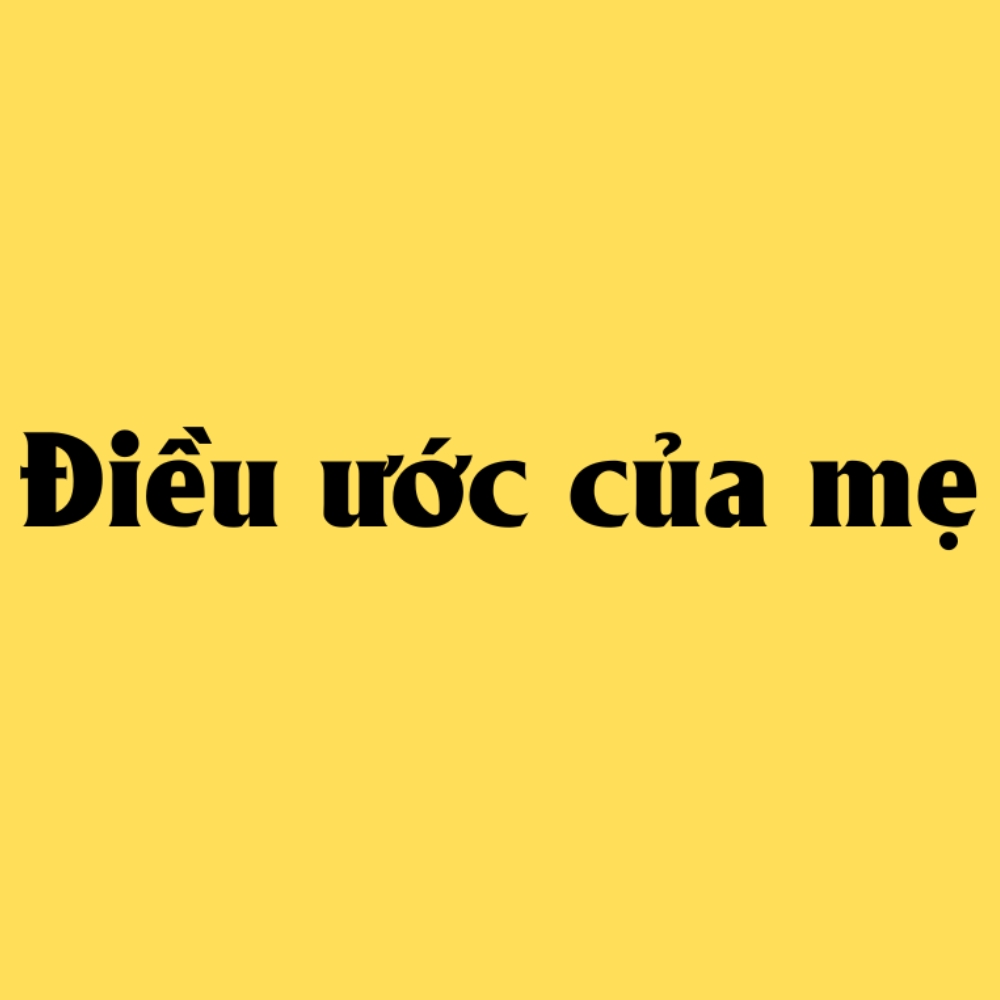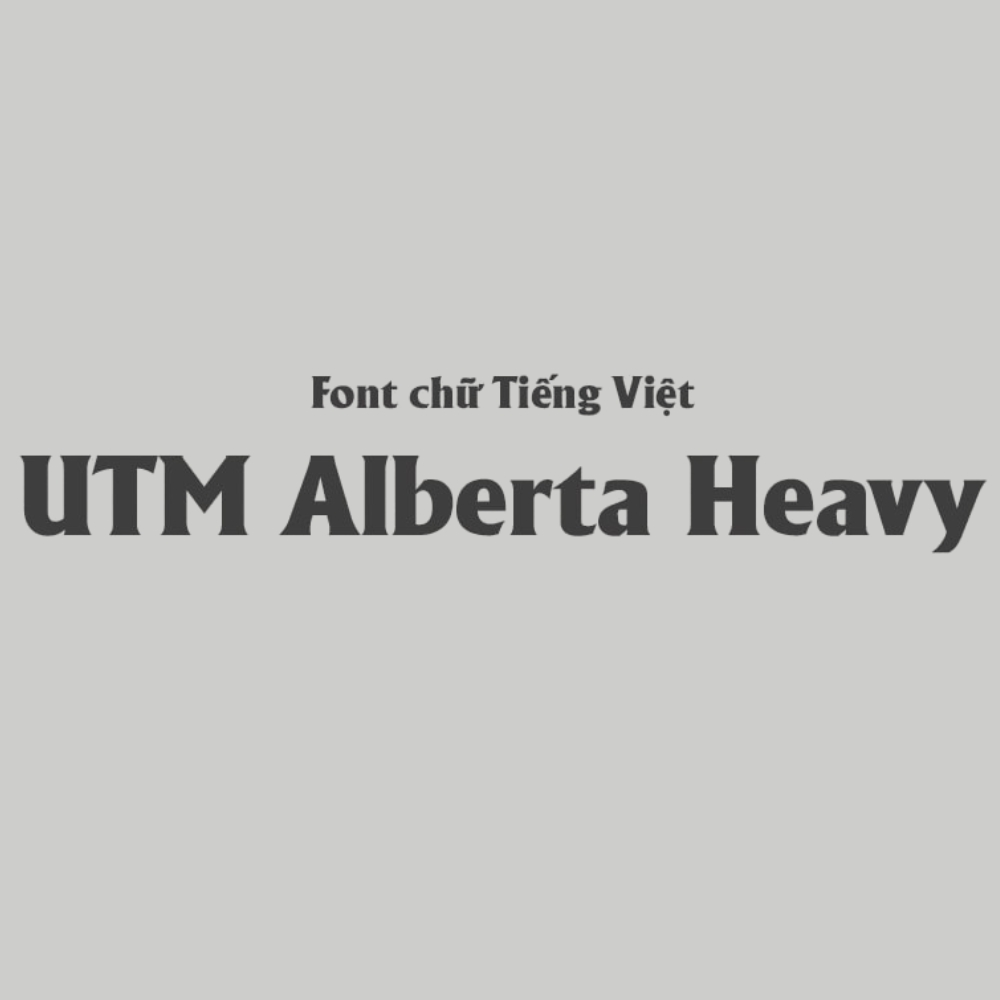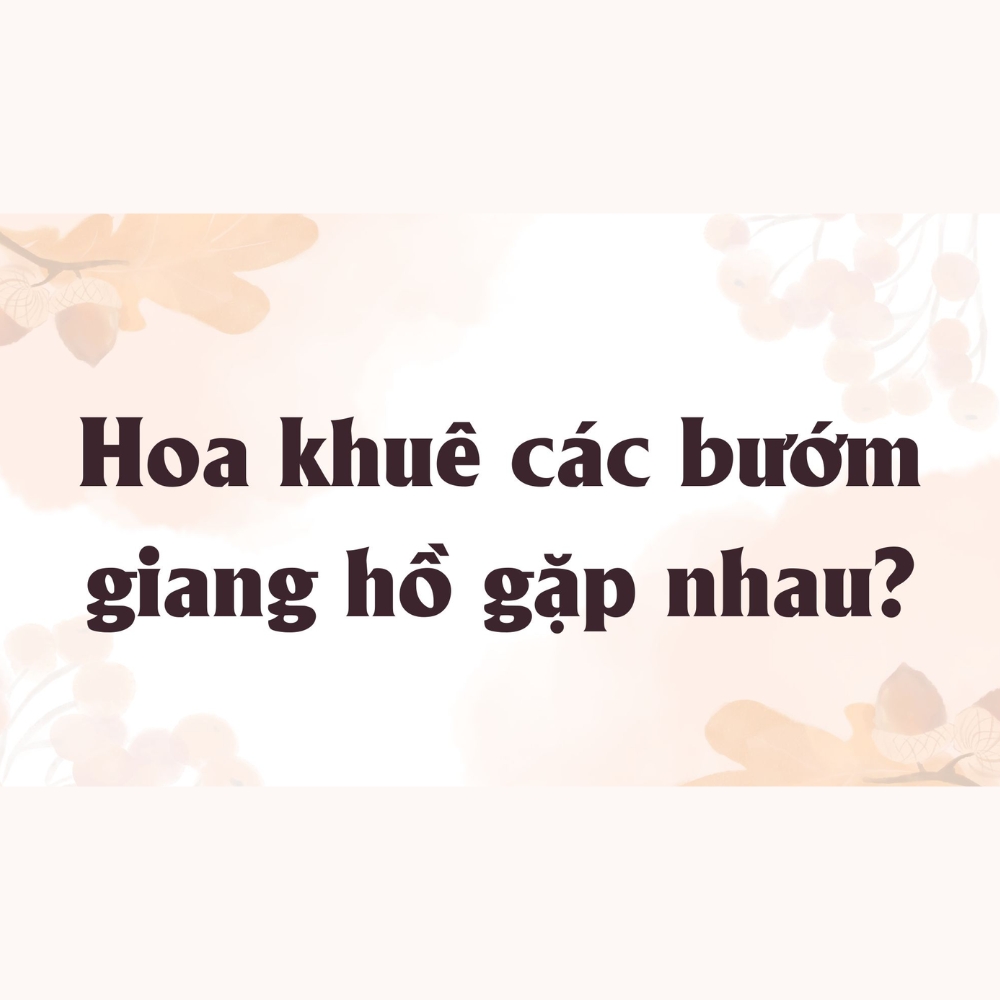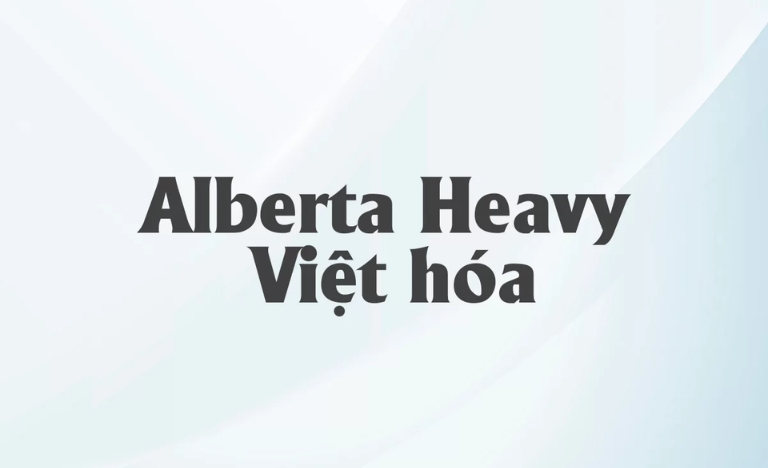
UTM Alberta Heavy là một trong những thành viên nổi bật của gia đình font chữ UTM (Unicode Tiện Nghi), được thiết kế với độ đậm nét cao, mang lại sự vững chãi và chuyên nghiệp cho văn bản. Sự xuất hiện của font Việt hóa UTM Alberta Heavy giúp người làm thiết kế tại Việt Nam có thêm phương án trình bày tiêu đề rõ ràng, không gặp lỗi hiển thị ký tự có dấu.
Đặc điểm nhận diện của font Việt hóa UTM Alberta Heavy
Dòng font này sở hữu cấu trúc không chân với các đường nét dày dặn, tạo nên sự tin cậy và minh bạch trong trình bày thông tin. Khác với các kiểu chữ mảnh mai, font chữ Việt hóa UTM Alberta Heavy tập trung vào khả năng thu hút thị giác từ xa, giúp các thông điệp chính trở nên tách bạch và dễ tiếp nhận. Việc tối ưu hóa bảng mã Unicode giúp các dấu thanh tiếng Việt được đặt ở vị trí cân đối, duy trì vẻ đẹp hiện đại và tính đồng nhất của bộ chữ gốc.
Sự ổn định của UTM Alberta Heavy còn thể hiện qua khả năng hiển thị tốt trên nhiều chất liệu khác nhau. Dù được in ấn trên bạt quảng cáo, khắc trên kim loại hay hiển thị trên màn hình kỹ thuật số, các cạnh chữ vẫn giữ được độ sắc sảo, không bị nhòe mờ. Đây là lựa chọn phù hợp cho những hạng mục thiết kế đòi hỏi tính ứng dụng cao và phong cách hiện đại, tối giản.
| Phân loại phong cách | Sans-serif / Bold / Modern |
| Mục đích phù hợp | Tiêu đề, Bảng hiệu, Poster, Heading hồ sơ |
Gợi ý trình bày: Vì UTM Alberta Heavy có độ đậm rất lớn, bạn nên dành font này cho các tiêu đề chính hoặc các con số quan trọng. Việc phối hợp cùng một font chữ mảnh và thoáng cho phần nội dung phụ sẽ giúp bản thiết kế đạt được sự cân bằng, tránh cảm giác nặng nề cho người xem.
03 Ứng dụng phổ biến của font UTM Alberta Heavy trong ngành xây dựng
Nhờ vẻ ngoài vững chãi và độ rõ nét cao, bộ font này được ứng dụng linh hoạt trong nhiều khâu vận hành và quảng bá dự án kiến trúc:
- Bảng tên và biển chỉ dẫn công trình: Sử dụng font Việt hóa UTM Alberta Heavy free cho biển hiệu tại các khu nhà lắp ghép, homestay hoặc văn phòng container giúp khách hàng dễ dàng nắm bắt thông tin từ khoảng cách xa.
- Tiêu đề hồ sơ năng lực và Profile dự án: Giúp doanh nghiệp thể hiện sự chuyên nghiệp và năng lực vững chắc thông qua cách trình bày các đề mục quan trọng một cách mạch lạc, ấn tượng.
- Ghi chú thông số kỹ thuật chính trên bản vẽ: Độ đậm của font chữ này giúp các số hiệu quan trọng trên bản vẽ CAD trở nên nổi bật, hỗ trợ đội ngũ thi công tra cứu thông tin nhanh chóng và chính xác.
03 Lưu ý khi sử dụng font chữ Việt hóa UTM Alberta Heavy
Để khai thác hiệu quả vẻ đẹp của bộ font này mà không làm ảnh hưởng đến thẩm mỹ chung của bản thiết kế, người dùng nên lưu tâm một số kinh nghiệm sau:
- Kiểm soát khoảng cách ký tự (Kerning): Do nét chữ dày, các chữ cái có xu hướng trông sát nhau. Bạn nên điều chỉnh nới rộng khoảng cách một chút để chữ không bị bết dính khi in ấn ở kích thước nhỏ.
- Tránh sử dụng cho đoạn văn bản dài: Tuyệt đối không dùng UTM Alberta Heavy cho các đoạn nội dung chi tiết hay thuyết minh dự án dài vì sẽ gây mỏi mắt và làm mất đi trọng tâm của bản thiết kế.
- Lựa chọn màu sắc phù hợp: Font chữ đậm phát huy hiệu quả thị giác cao khi đặt trên các nền màu đơn sắc hoặc có độ tương phản rõ rệt, giúp các đường nét vuông vức của chữ được tôn vinh rõ ràng.